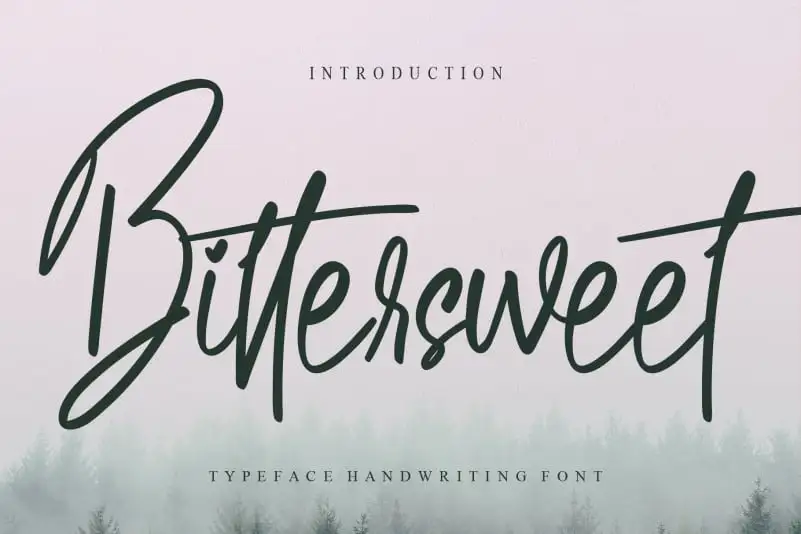
Bittersweet Script Font – Download Grátis
A fonte ‘Bittersweet Script Font’ é uma escolha excepcional para quem busca uma experiência única e envolvente no design de gráficos. Ideal tanto para criar texturas fluidas como para trabalhar com headlines impactantes, essa fonte traz nuances sutis e emoções sutis ao seu trabalho. Desenvolvida pela designer creativeletter, a ‘Bittersweet Script Font’ oferece uma paleta de sentimentos através de linhas suaves e traços delicados que permitem criar texturas arredondadas e linguagem visuais profundamente significativas. Uma das suas características mais notáveis é o grau incrivelmente realista de detalhes em cada letra, onde cada caractere parece ter sido escrita por mão humana. Esta característica oferece um nível inigualável de personalização e expressão ao seu design, permitindo que você personalize sua marca ou projeto de acordo com suas necessidades específicas. Englobando a estética elegante e sofisticada do script com um toque de leveza, esta fonte é perfeita para uma variedade de aplicações: desde designs de logomarca e revistas impressas até gráficos digitais e redes sociais. A ‘Bittersweet Script Font’ traz uma sensação de intimidade e autenticidade ao seu trabalho de design, tornando-a um verdadeiro atalho para uma jornada criativa envolvente.